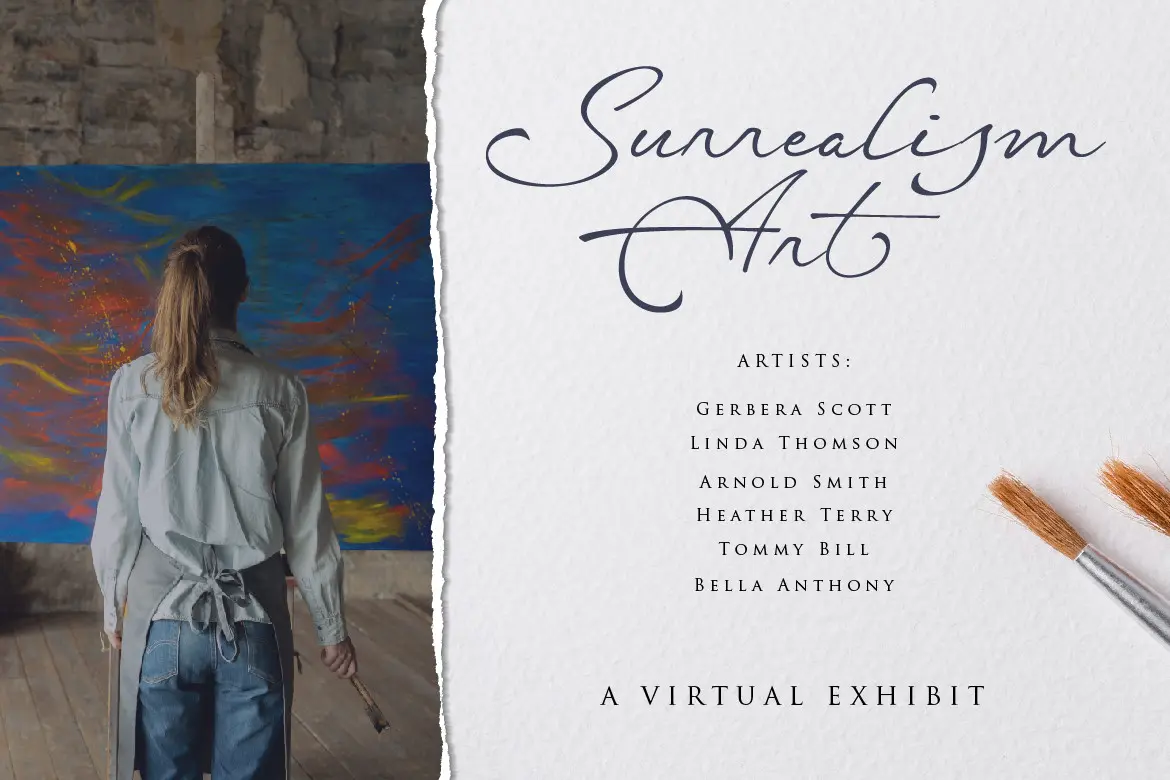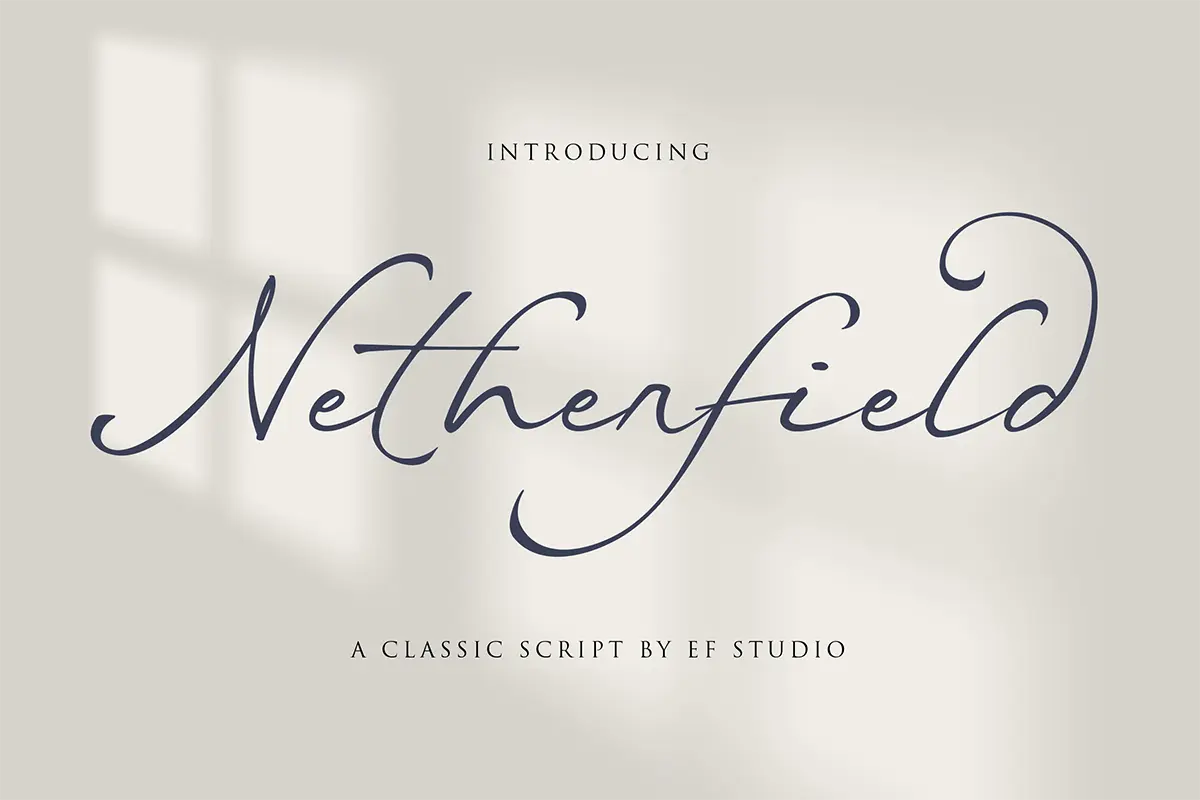
فونت اسکریپت دستنویس روان و شیک
فونت Netherfield یک فونت اسکریپت دستنویس بسیار ظریف، روان و شیک است که جلوهای الگانت و کلاسیک به طراحیهای شما میبخشد. این فونت برای پروژههایی که نیاز به لمس دستنویس و شخصی دارند، انتخابی عالی است و میتواند حس گرمی و صمیمیت را به آثار شما اضافه کند.
⭐ ویژگیهای محصول
- سبک: اسکریپت دستنویس روان و ظریف
- حس و حال: الگانت، کلاسیک و دلنشین
- مناسب برای: دعوتنامههای عروسی، کارتهای تشکر، نقلقولها، کارتهای تبریک، لوگوها و کارتهای ویزیت
- افزودن جلوه دستنویس طبیعی به هر نوع طراحی
🎯 موارد استفاده
- طراحی دعوتنامههای عروسی و مراسم رسمی
- ساخت کارتهای تشکر و تبریک
- استفاده در لوگوهای ظریف و برندهای لوکس
- افزودن حس شخصی و دستنویس به پروژههای گرافیکی